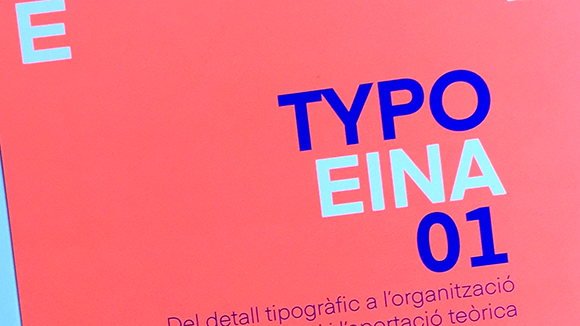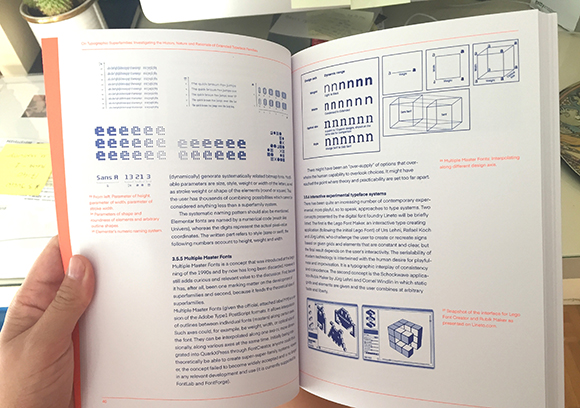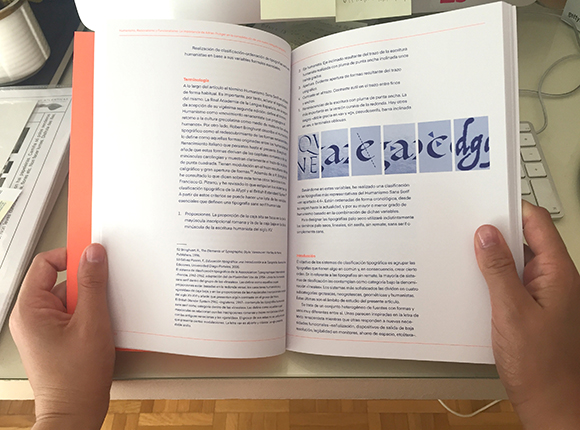
De un tiempo a esta parte no me cabe duda de que los recursos en torno a la tipografía han aumentado de forma considerable en este país: Páginas web, editoriales especializadas o programas didácticos de centros educativos, han permitido que el nivel general de “conciencia tipográfica” en todos los sectores implicados en su uso, divulgación o enseñanza se haya visto generosamente elevado.
No obstante, entre todas las iniciativas que han ido apareciendo a lo largo de estos años, echaba a faltar un espacio de reflexión, análisis e investigación que partiera del ámbito educativo y que conjugara los contenidos generados por los propios docentes como los realizados por los alumnos a partir de trabajos desarrollados dentro del programa didáctico.
En este sentido, tengo que saludar la iniciativa que ha puesto en marcha por EINA (Centre Universitari de Disseny i Art de Barcelona) y que nace de su reputado Máster de Tipografía Avanzada. Se trata de una publicación llamada Typo Eina 01, de la que acabo de recibir su primer número, y con el que pienso se completa el espectro de posibles contribuciones divulgativas que sobre tipografía echaba en falta.
Efectivamente en este primer número encontramos desde artículos de corte histórico como los dedicados a la figura de nuestro añorado Josep Maria Pujol (1947-2012) hasta proyectos de investigación como el que revisa el concepto de superfamilias tipográficas o nos muestra el desarrollo de la letra humanista cursiva.
Artículos generado a partir de las actividades del Master, que se complementan con muestras de alfabetos creados en el mismo y que conforman una publicación a la que deseo un brillante porvenir, ya que como expresé anteriormente, pienso que era el tipo de publicación que faltaba en nuestro saludable panorama tipográfico.